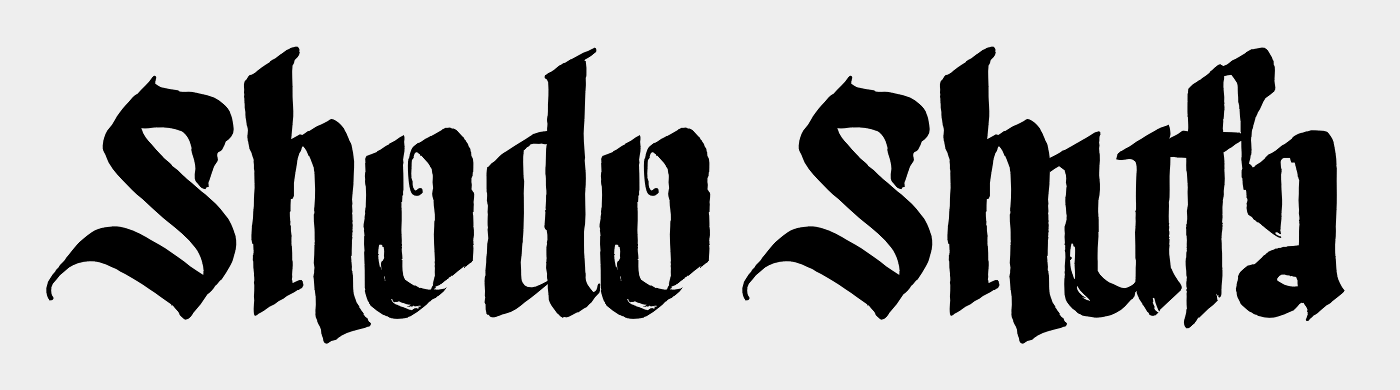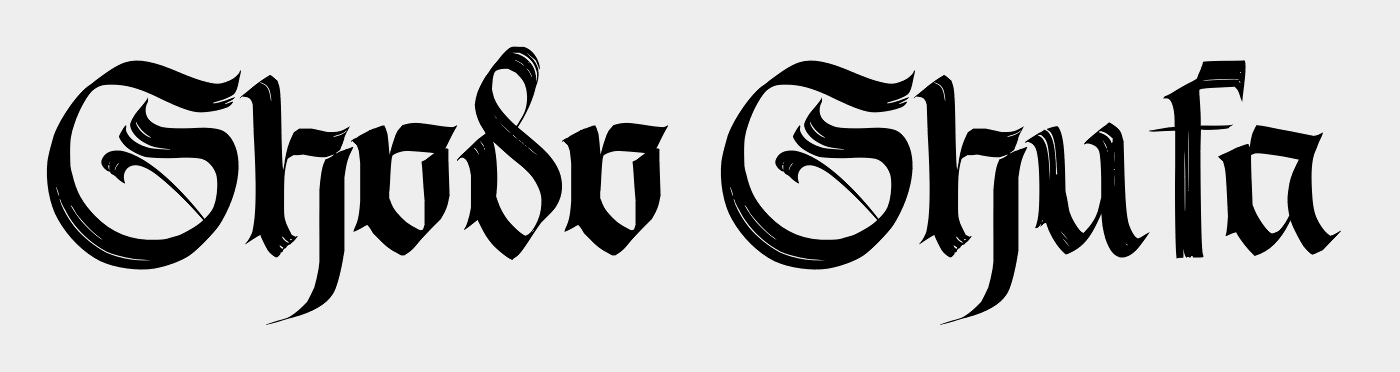
ich möchte einer Headline die in einer Fraktur geschrieben sein soll und deutsche Wörter enthält einen japanischen Touch geben durch die ikonische Pinselführung der Kanji aus Japan.
Kennt vielleicht jemand eine passende Font?
Und dann wäre da noch diese (finde ich aber nicht so toll, weil da offenbar jemand nicht weiß, wie man den Pinsel hält :party: ):
Andersherum finde ich es übrigens attraktiver – aber dann kann es ja wieder kaum einer lesen ... http://luc.devroye.org/fonts-64713.html